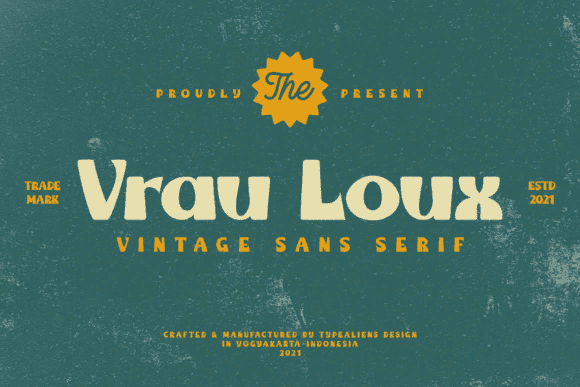
Vrau Loux
- это шрифт, воплощающий подлинность и очарование.
Он может поддерживать как винтажный, так и современный дизайн и подходит для оформления логотипов, значков, футболок, этикеток и т.д.